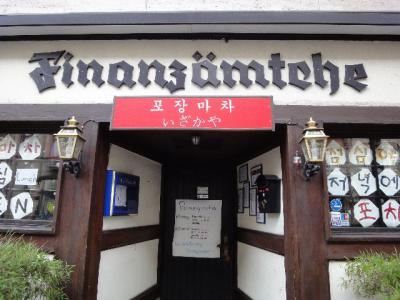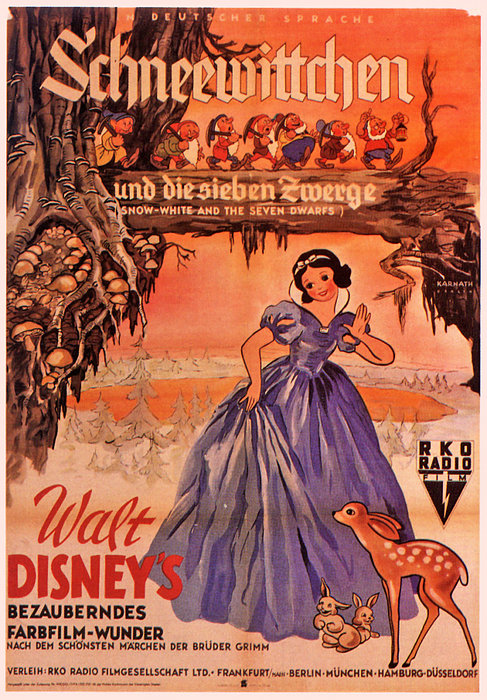
Schriftmuster Tannenberg
Ich denke, dass man die Absicht einer "Kampagne" immer noch am einfachsten in den Worten erkennen kann, die sie verwendet.
Das ist nur die Taktik der Kampagne, aber nicht die Strategie die dahinter steckt und schon gar nicht die „Steuerung“. Nach zwei oder drei Hopps sind viele der Ausführenden schon von den Quellen abgehängt und wissen gar nicht mehr wem sie was tun. Das geht mir in meinem Bereich auch öfters so. Allerdings frage ich dann gerne nach ... Ich bin nun mal sehr neugierig was solche Dinge anbetrifft.
Langam habe ich ein richtig schlechtes Gefühl, und begreife immer mehr, dass "Freier Wille" nichts weitere als eine schöne Theorie ist, und man eigentlich hinterher niemanden einen Vorwurf machen kann, wenn dieser Ferngesteuerte freie Wille dann in eine Katastrophe wie dem 3. Reich führte.
Das natürlich auch, allerdings gibt es ebebn auch noch etliche Hauptbahnhöfe, die das mir vergleichsweise kleineren Blessuren überstanden haben.
KdF ist aber dann Volkswagen geworden. Da denke ich an Futura. Und bei den Verkehrsnetzen an die Schriften nach DIN 1451. Eisenbahn wäre eigentlich auch DIN 1451 und Co, wird Dir auch Catfonts sicher bestätigen, aber irgendwie blieb da die Tannenberg auch noch bei mir hängen.